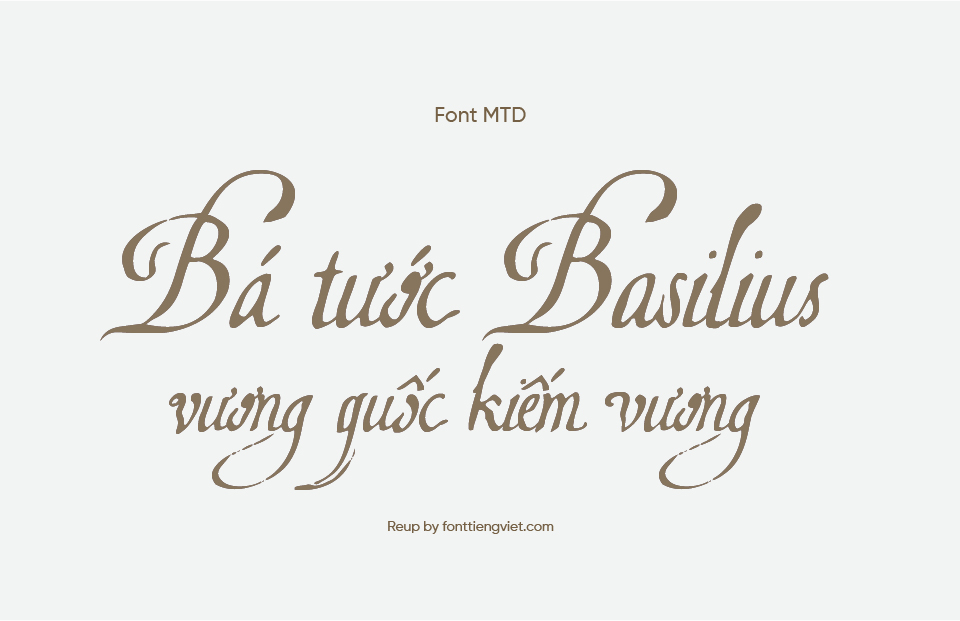
Font Việt hóa MTD 1613 Basilius – Bộ Font Chữ Cổ Điển Sang Trọng
Giới thiệu về Font Việt hóa MTD 1613 Basilius
Trong thế giới thiết kế đồ họa, việc lựa chọn một bộ Font Chữ phù hợp đóng vai trò quyết định đến linh hồn của tác phẩm. Font Việt hóa MTD 1613 Basilius là một cái tên nổi bật mang phong cách Serif cổ điển, được lấy cảm hứng từ các bản in thế kỷ 17. Bộ font này không chỉ giữ trọn vẹn nét tinh tế, quyền quý của nghệ thuật Typography phương Tây mà còn được tối ưu hóa hoàn toàn cho tiếng Việt. Nhờ đó, các nhà thiết kế tại Việt Nam có thể dễ dàng sử dụng trong các dự án đòi hỏi sự trang trọng và tính thẩm mỹ cao mà không lo lỗi hiển thị dấu câu.
Đặc điểm nổi bật của Font Việt hóa MTD 1613 Basilius
Thiết kế mang đậm tính nghệ thuật
Đặc trưng của Font Việt hóa MTD 1613 Basilius nằm ở các đường nét thanh mảnh kết hợp cùng chân chữ cứng cáp, tạo nên sự cân bằng hoàn hảo giữa nét truyền thống và hiện đại. Kiểu dáng của font gợi nhớ đến các văn bản hành chính hoàng gia hoặc những cuốn sách cổ quý hiếm. Với độ tương phản nhẹ nhàng, bộ font này mang lại cảm giác dễ đọc và cực kỳ lôi cuốn thị giác.
Ứng dụng đa dạng trong giáo dục và thiết kế
Đối với học sinh và thầy cô giáo, bộ font này là lựa chọn lý tưởng để trình bày các bài tiểu luận, bìa giáo án hoặc chứng chỉ khen thưởng. Trong lĩnh vực thương mại, Font Việt hóa MTD 1613 Basilius thường xuyên xuất hiện trên bao bì sản phẩm cao cấp, thiệp mời sự kiện và logo thương hiệu thời trang. Khả năng hiển thị sắc nét giúp bộ font này hoạt động tốt trên cả bản in lẫn màn hình kỹ thuật số.